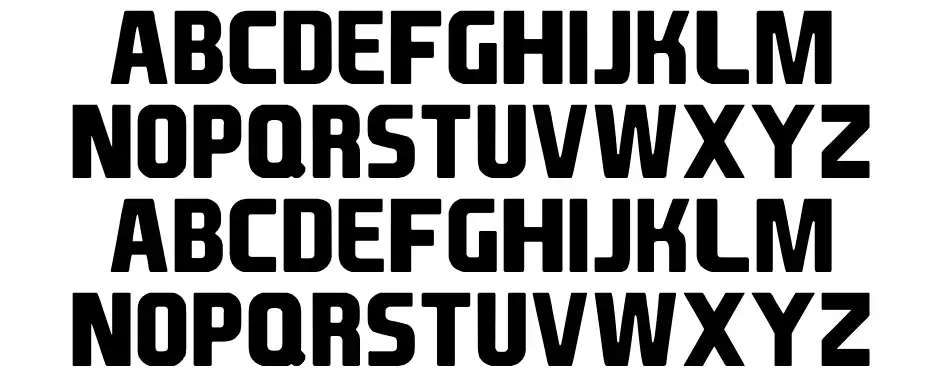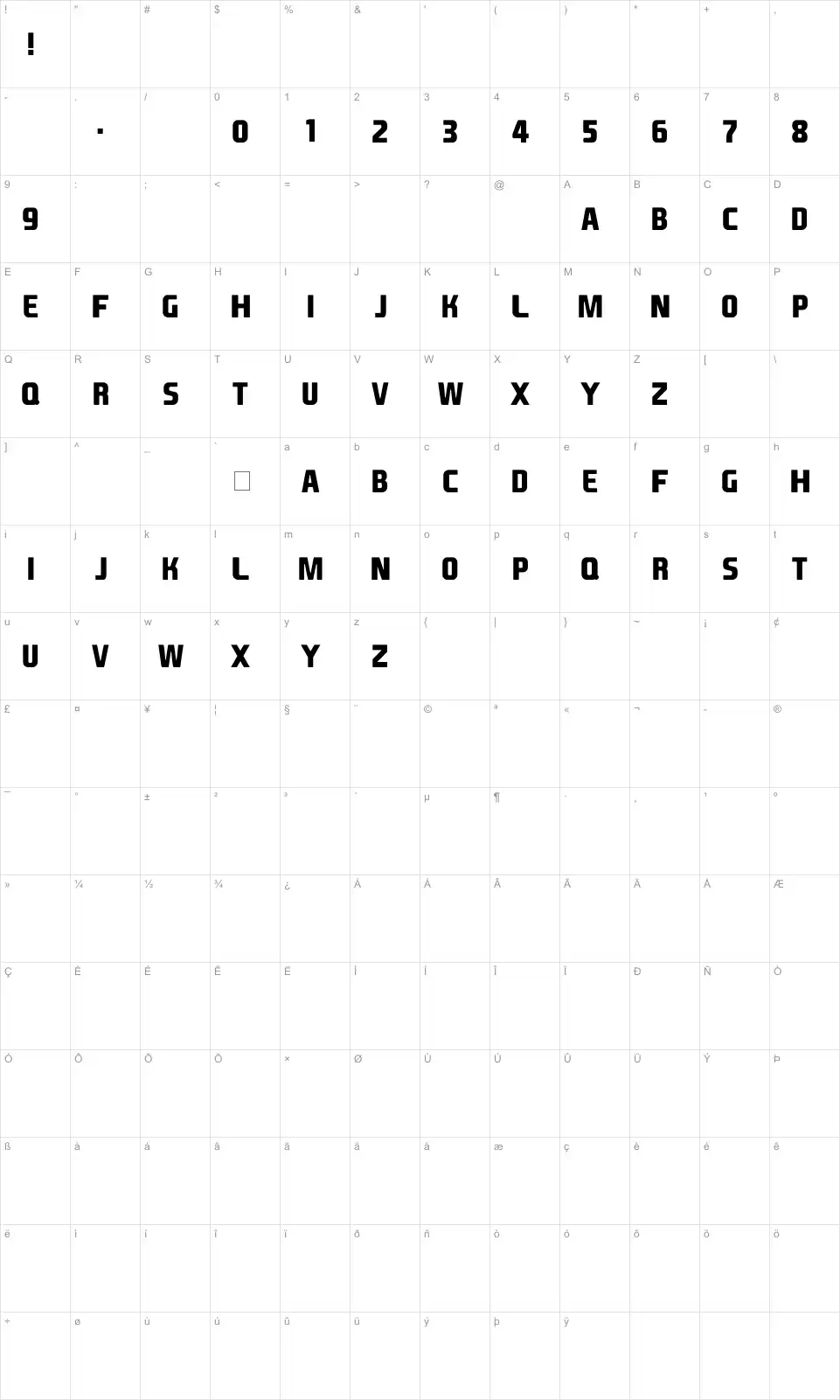
EA Font – Download Grátis
A fonte EA Font, criada pelo designer Billy Smith, está disponível para download e visualização online. Se você está procurando pela fonte EA Font, aqui está uma excelente oportunidade. Seja para uma aplicação criativa ou um projeto profissional, a EA Font oferece um toque tecnológico e moderno. Este tipo de fonte é ideal para elementos de tecnologia, mas também se adequa a várias outras categorias. A EA Font é licenciada sob uma licença gratuita, disponível em formato TTF. Adicionada recentemente em 12 de julho de 2022, a fonte já recebeu 2787 downloads e não excede os 8 KB de tamanho, garantindo a eficiência e a rapidez em qualquer aplicação. Convidamos você a descobrir como a EA Font pode transformar o seu design.